Font chữ Graffiti
Font chữ Aid được thiết kế dành cho những người làm nghệ thuật. Nó là một sự lựa chọn tuyệt vời cho bất kỳ dự án hiện đại nào đòi hỏi một cái nhìn táo bạo và cảm nhận. Font chữ bao gồm chữ hoa, số và ký tự dấu chấm câu. Nó miễn phí cho sử dụng cá nhân.
Sprite Graffiti Font
Font chữ Sprite có 3 kiểu khác nhau và bạn có thể sử dụng nó khi bạn cần giao diện graffiti đó nhưng vẫn muốn duy trì mức độ dễ đọc. Font chữ này là miễn phí cho sử dụng cá nhân và thương mại và đi kèm với giấy phép máy tính để bàn và webfont.
MostWanted Graffiti Font
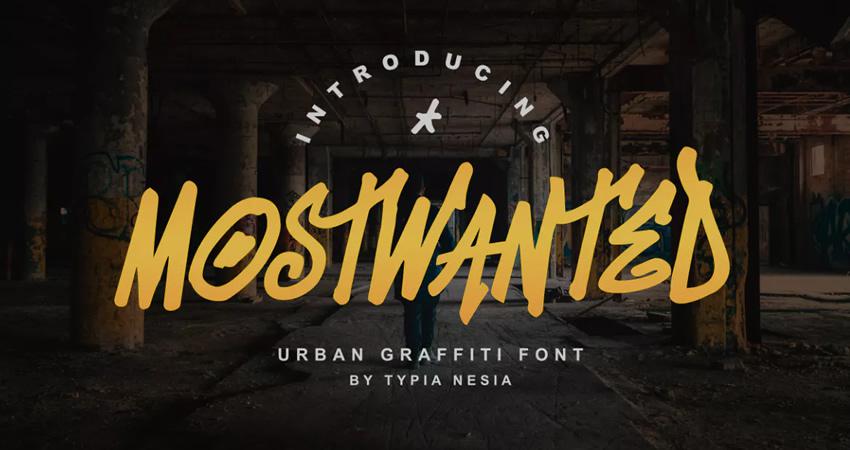
MostWanted Graffiti Font là một font chữ graffiti hơi hướng hiện đại có cả chữ hoa và chữ thường. Bạn có thể trộn và kết hợp chúng để tạo ra một thiết kế logo độc đáo. Font chữ được bao gồm như là một phần của thuê bao Envato Elements của bạn.
Tag Type Free Font
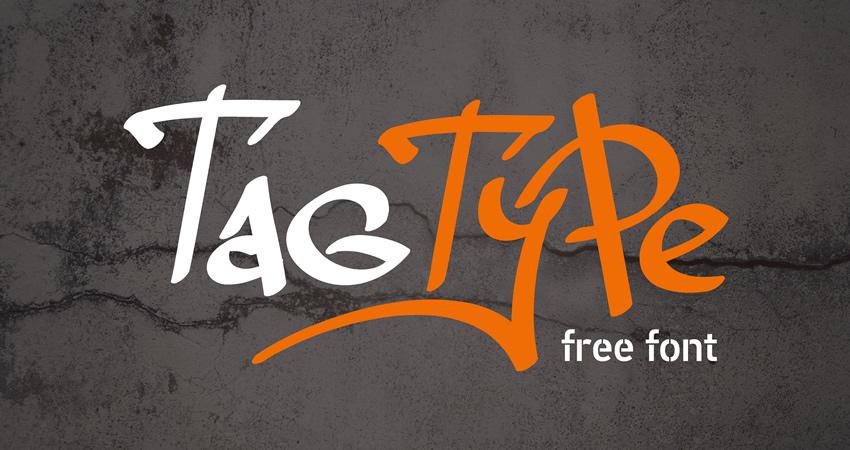
Tag Type Free Font có chữ hoa và chữ thường và bạn có thể tải xuống font chữ và sử dụng nó trong các dự án cá nhân miễn phí. Font chữ cũng bao gồm các ký tự dấu chấm câu và các ký tự.
BlowBrush Font
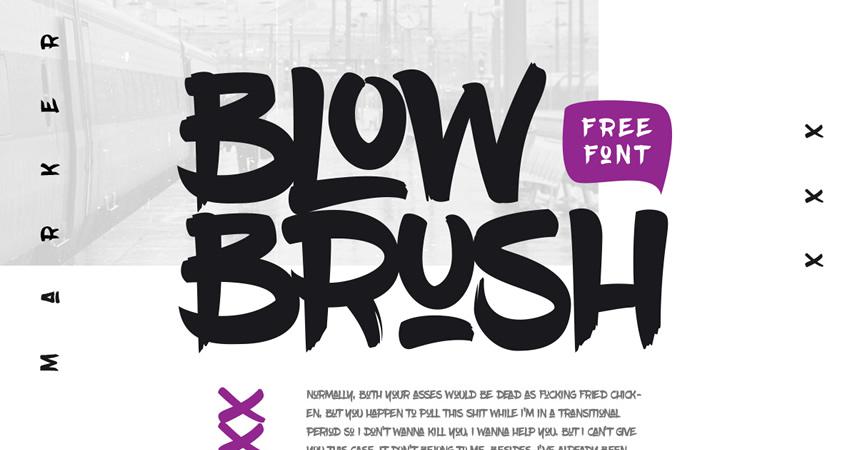
Font chữ BlowBrush là một font chữ viết tay, kiểu chữ đánh dấu hoàn hảo cho bất kỳ dự án nào mà bạn cần một cái nhìn táo bạo và cảm nhận. Font chữ đi kèm với một bộ đầy đủ các ký tự trên, số, 22 chữ, một lựa chọn các ký tự đặc biệt và một số biến thể.
Graffiti Front
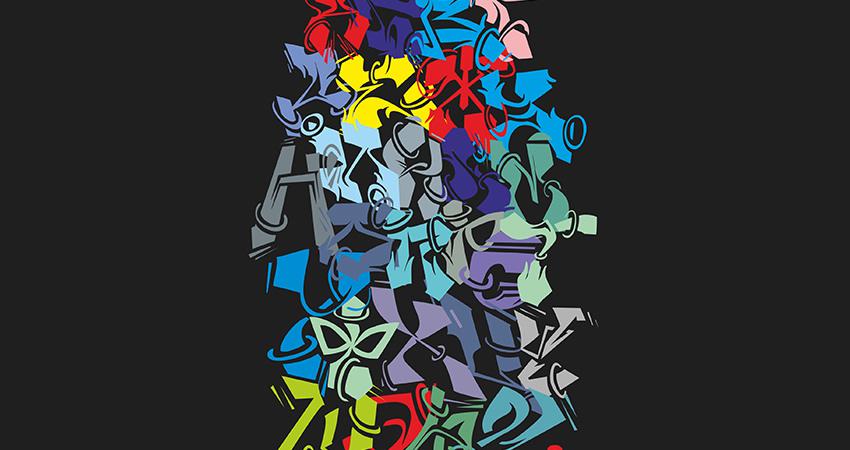
Font chữ Graffiti là một cách tuyệt vời để trang trí các thiết kế poster phim của bạn. Nó có một bộ đầy đủ các ký tự và có thể được sử dụng trong các dự án cá nhân và thương mại.
Watch Graffiti Font
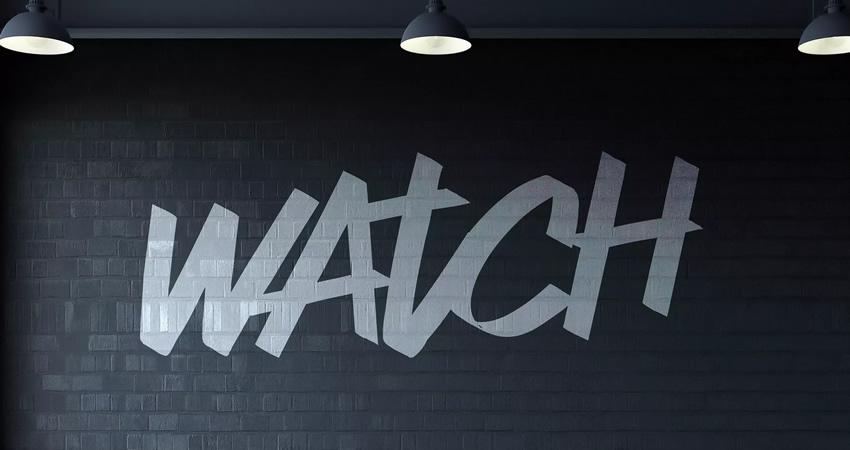
Font chữ graffiti Watch là một phần của Envato Elements của bạn và là một lựa chọn hoàn hảo cho thiết kế poster, tiêu đề & tiêu đề, bìa tạp chí, v.v.
Sloppy Paint Font
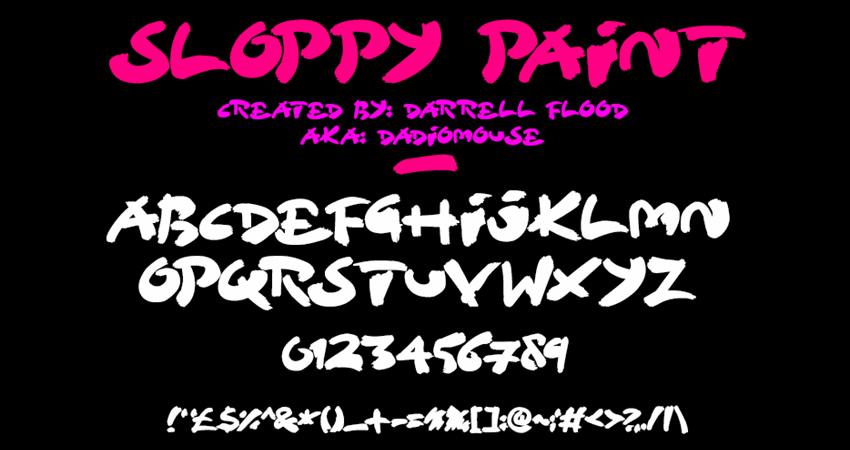
Font chữ Sloppy Paint miễn phí cho sử dụng cá nhân và bao gồm một bộ đầy đủ các ký tự in hoa, chữ cái và ký hiệu dấu chấm câu.
The Graffiti Font
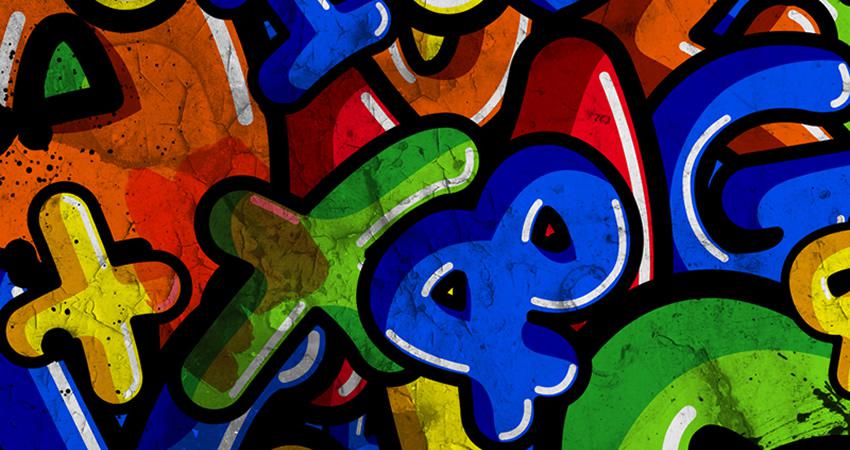
Font chữ Graffiti này có phiên bản màu đen và trắng cũng như phiên bản màu. Bạn có thể tải xuống dưới dạng tệp PNG và sử dụng nó cho các dự án cá nhân và thương mại.
Don Graffiti Font
Font chữ Don Graffiti được lấy cảm hứng từ graffiti trường học cũ. Nó miễn phí cho các dự án cá nhân và thương mại và là một lựa chọn tuyệt vời cho áp phích phim, hiển thị, bìa tạp chí và tiêu đề.
Baling Ink Font
Font chữ Baling Ink là một phần của thuê bao Envato Elements của bạn. Nó có một font chữ biểu cảm và một sự lựa chọn tuyệt vời cho các dự án xây dựng thương hiệu hoặc thiết kế muốn truyền tải một cảm giác hiện đại và thành thị.
Brushed Font
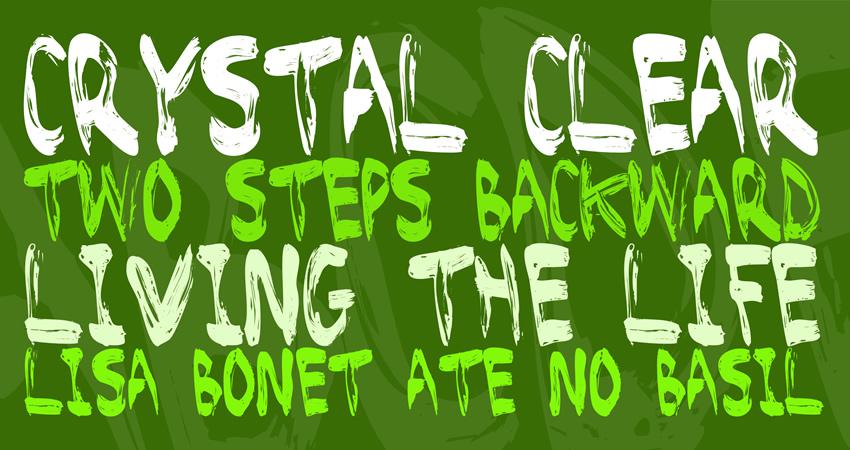
Fonted Fonted là miễn phí cho sử dụng cá nhân. Nó bao gồm chữ hoa, số và ký tự dấu chấm câu.
Humblle Rought Font
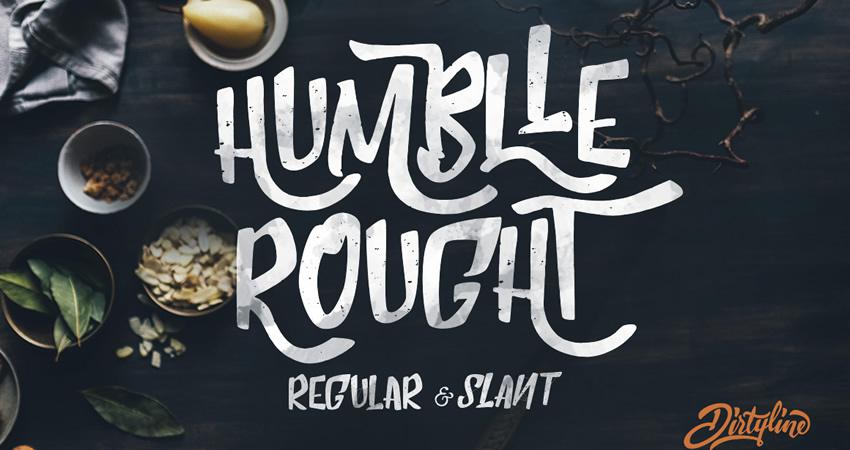
Font chữ graffiti này bao gồm một phiên bản thông thường và nghiêng. Nó có một cái nhìn và cảm giác thô ráp vì vậy nó là một sự lựa chọn tuyệt vời cho các dự án thiết kế retro. Nó bao gồm các bộ ký tự tiêu chuẩn và thay thế và hỗ trợ đa ngôn ngữ.
Marker No2Hun Font
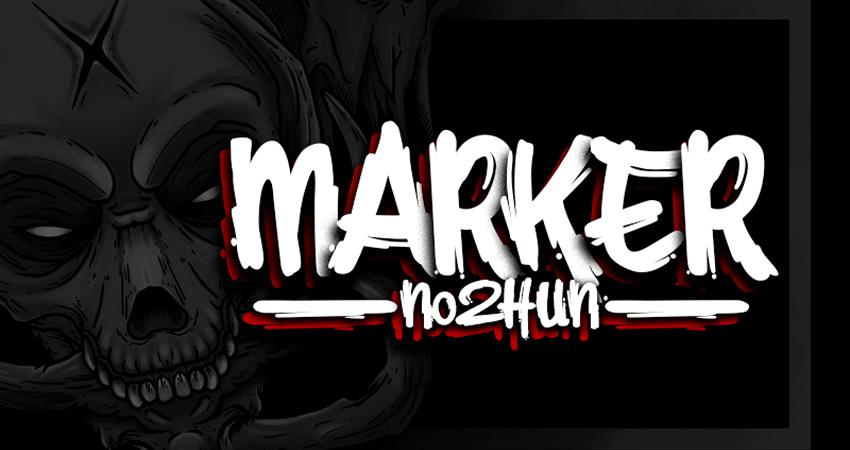
Font chữ Marker No2Hun miễn phí cho sử dụng cá nhân và bao gồm một bộ đầy đủ các chữ cái in hoa và chữ thường, số và ký tự dấu chấm câu. Một số thay thế cũng có sẵn.
Dexgraffiti Return Graffiti Font
Dexgra Bức tranh là một font chữ mới lạ, rất phù hợp cho các dự án đô thị hiện đại. Nó bao gồm một bộ đầy đủ các chữ cái viết hoa và chữ thường cũng như số và dấu chấm câu.
Fusterd Brush Font
Fusterd Brush Font có kiểu dáng và cảm giác thanh lịch. Bạn có thể sử dụng nó cho các dự án cá nhân và thương mại. Các font chữ đi kèm với chữ hoa và chữ thường, số, và kiểu cách.